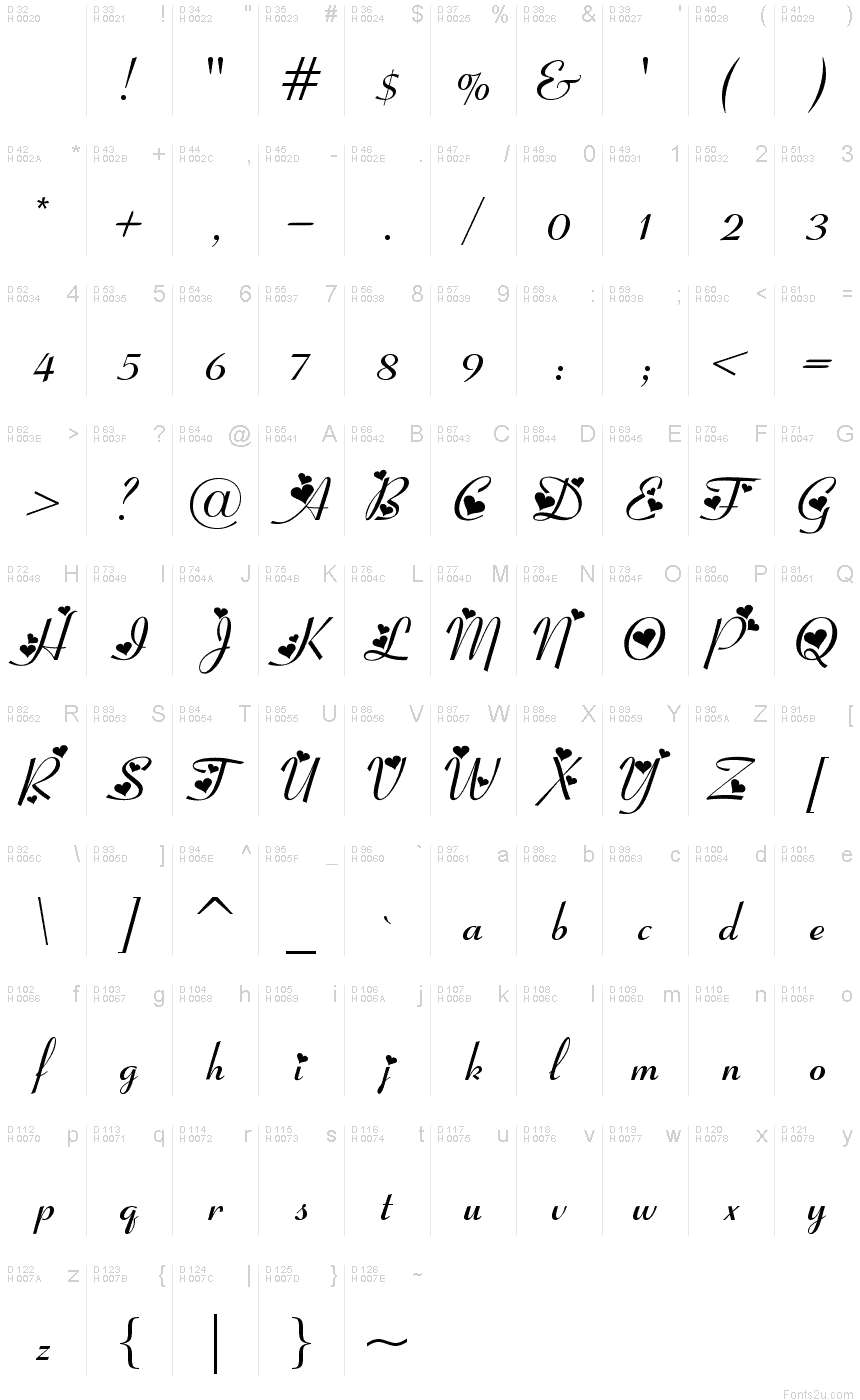
Fiolex Girls to bezpłatny, romantyczny krój pisma typu script z zabawnym, walentynkowym akcentem. Płynne, kaligraficzne pociągnięcia falują w linii, a wyraziste serduszka wyskakują z liter niczym naklejki na liście miłosnym. Krzywe wyglądają jak rysowane tuszem, nadając wszystkiemu, co napiszesz, flirciarski i osobisty charakter, którego trudno nie zauważyć.
Użycie Fiolex Girls na kartkach walentynkowych, dekoracjach ślubnych, wydrukach z cytatami o miłości, zaproszeniach, przywieszkach prezentowych czy opakowaniach słodyczy natychmiast buduje delikatny, pełen czułości nastrój. Ten darmowy font najlepiej sprawdza się w nagłówkach lub jako akcent, w połączeniu z przejrzystym, bezszeryfowym krojem w tekście głównym, co zapewnia Twoim projektom czytelność i urok.
Fiolex Girls